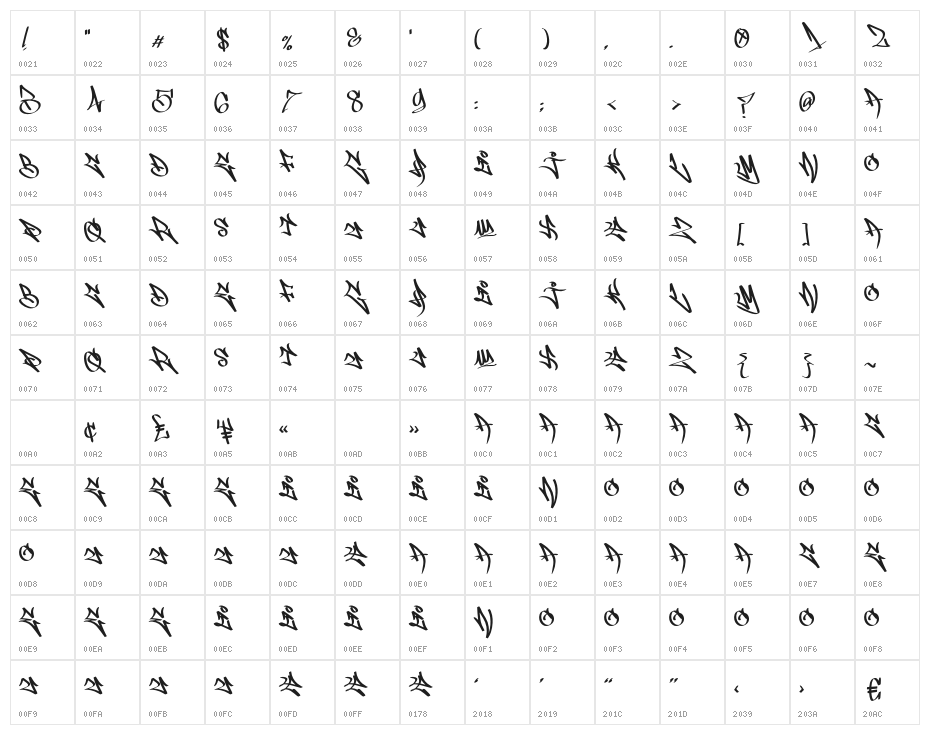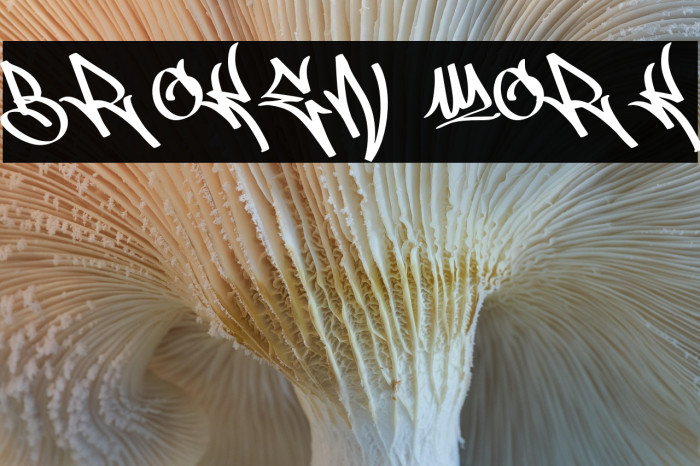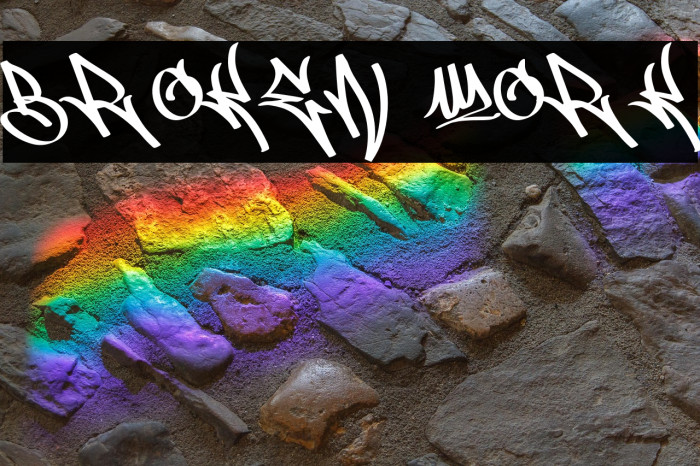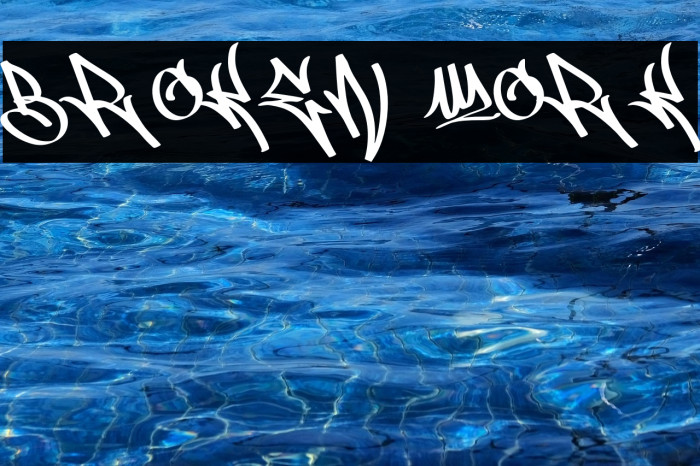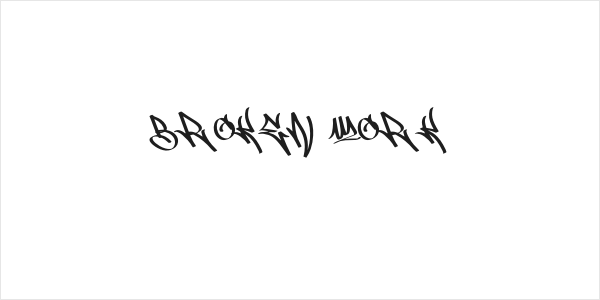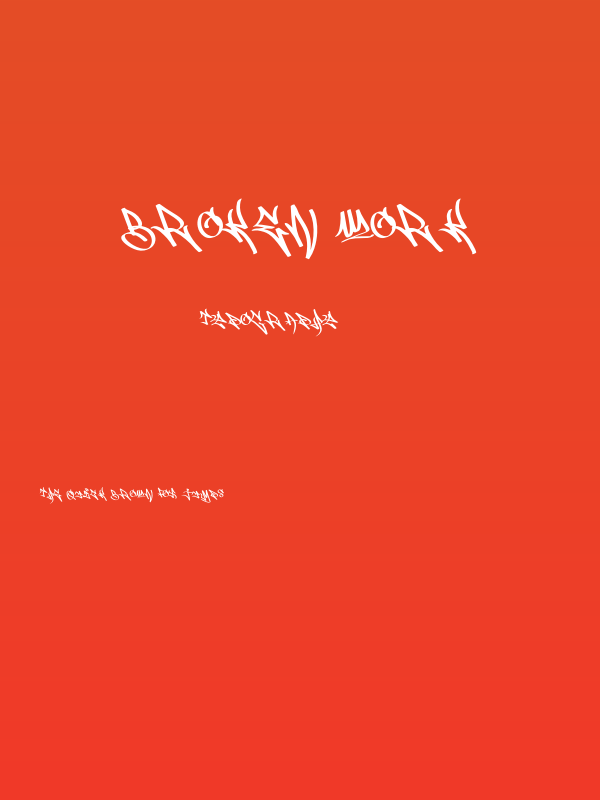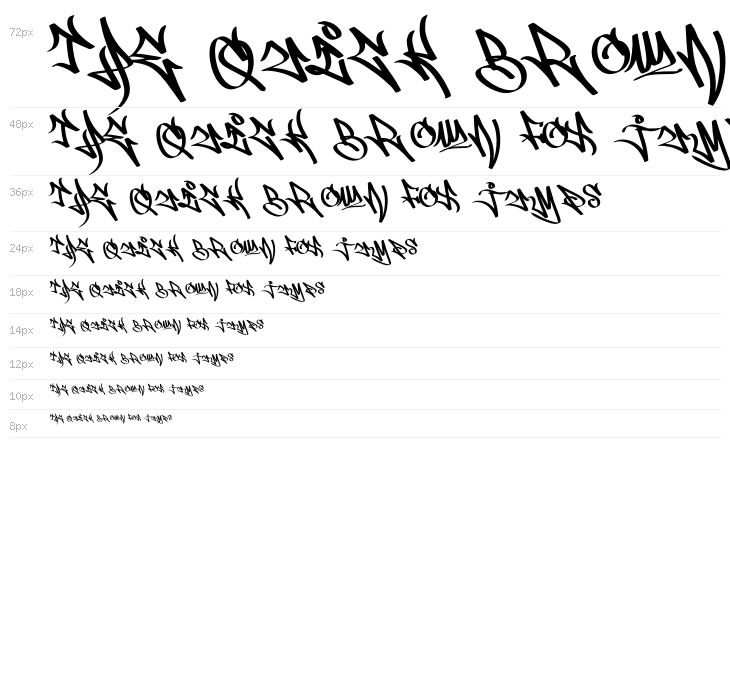
Broken Work Font
✎ Graffiti
| Categorie | Graffiti |
| Stile generale | Urban, Rebellious, Energetic |
| Caso d'uso | Logos, Posters, Album Covers |
| Progetti proposti | Ideal for street art designs, urban-themed posters, music album covers, and edgy branding projects. |